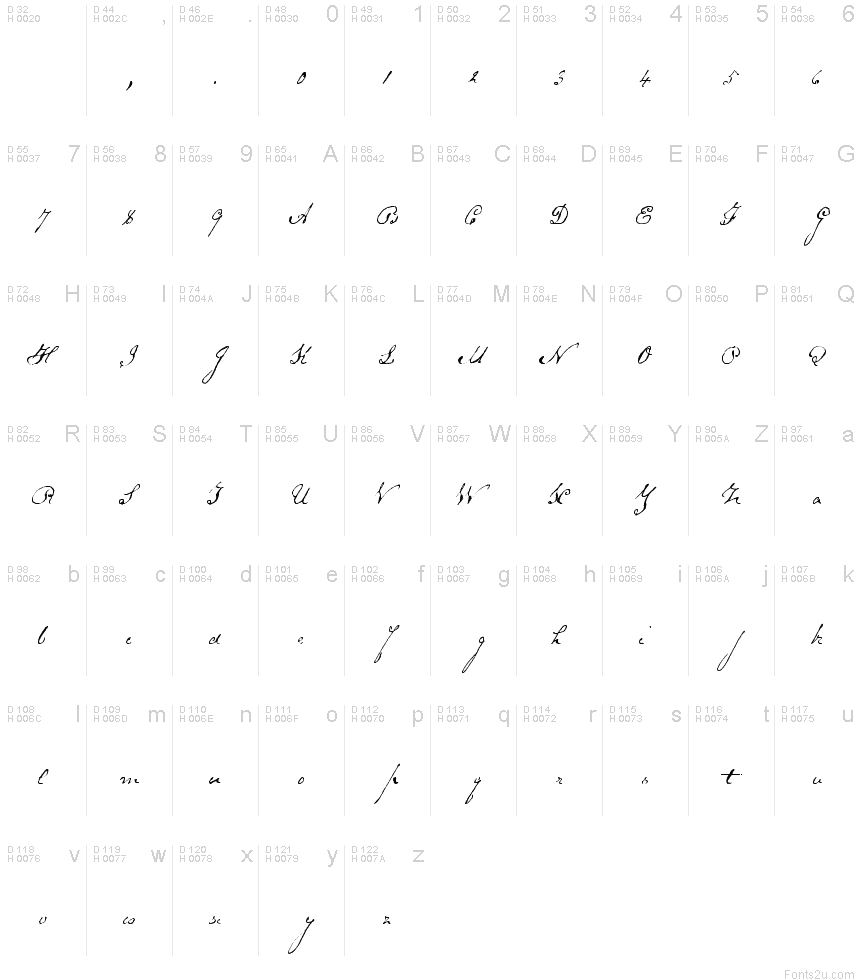
Schoon è un carattere manoscritto gratuito con un ritmo libero e fluido, dal sapore leggermente rétro. Le lettere presentano lunghi tratti d'ingresso e curve arrotondate; il risultato ricorda più una scrittura veloce a inchiostro che un rigoroso esercizio di calligrafia.
È ideale per il branding di boutique, menu di caffè, biglietti d'auguri, copertine di libri e titoli brevi su poster, dove un font gratuito può conferire un tocco personale e immediato. Usalo per titoli, nomi su inviti o sul packaging quando desideri che i collegamenti fluidi e le ampie curve facciano la parte del leone nel design.